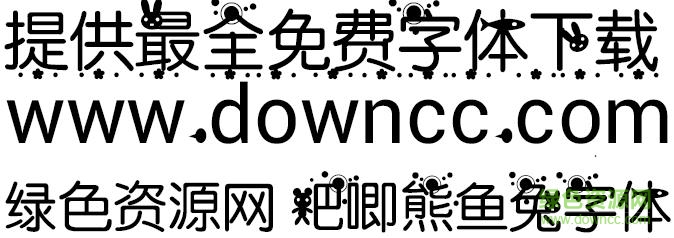
吧唧熊魚兔字體
吧唧熊魚兔字體的特色在于擁有魚和兔子在每一個字體中,讓你感受到十分有趣的效果,小兔子在每一個字的字里行間內(nèi)出沒,而且在英文字體中能夠帶來獨特的顯示效果呢!
吧唧熊魚兔字體小編點評
這款字體看著很舒服,如果是小孩子一定會一眼愛上這款字體,這款字體在一些娛樂節(jié)目中可以作為字幕字體作為使用,在書寫的時候也能夠給他人獨特的閱讀體驗!
吧唧熊魚兔體字體